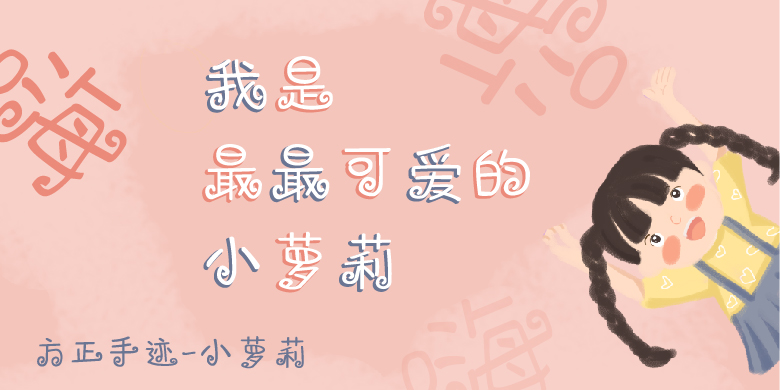
方正手迹-小萝莉体
字体品牌: 方正手迹 设计师:瞿颖 字体分类:创意书写 字体属性:精品字 字符集:大陆简体(GB2312-80) 发布时间: 2018
充满稚气的字形,卷曲的小挂件与字融为一体,恰似小女孩天真烂漫的个性中透出的玩皮。适用于少年儿童类的书刊、品牌广告和产品包装设计,以及社交网络的个性化用字。